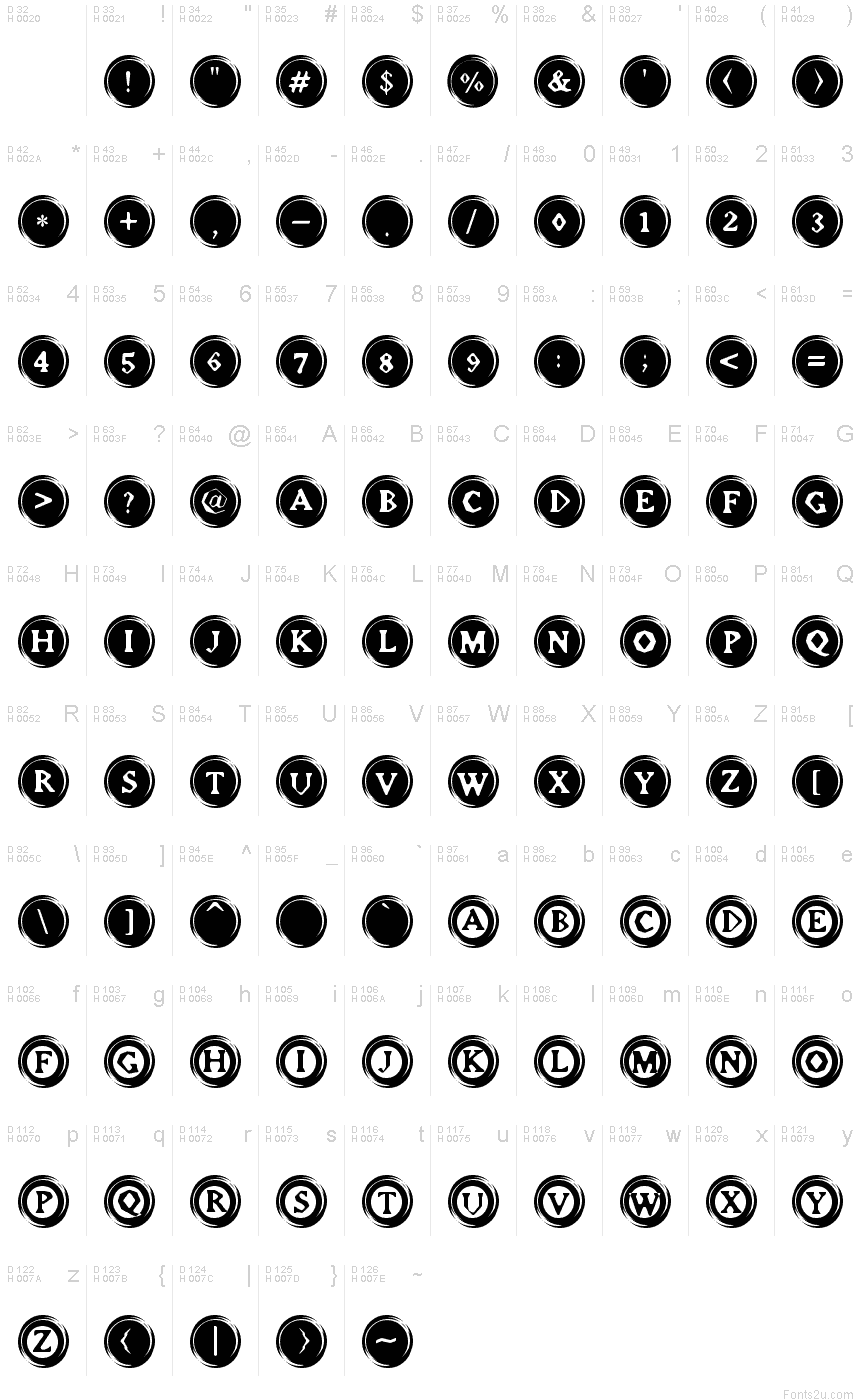
Elevator Buttons od OMEGA Font Labs to bezpłatny, dekoracyjny krój pisma, który przypomina rządek błyszczących, podświetlanych przycisków windy. Każdy znak umieszczony jest w gęstym czarnym okręgu z warstwowymi białymi obwódkami, tworząc mocny, „przyciskowy” rytm, który wręcz wyskakuje ze strony. Masywne, lekko nietuzinkowe litery przypominają połączenie panelu sterowania w stylu retro z automatem do gier, nadając nagłówkom wyczuwalną, interaktywną energię.
Wykorzystaj Elevator Buttons do błyskawicznego brandingu interfejsów gier, plakatów sci-fi, paneli sterowania, tytułów imprez tematycznych, grafik do escape roomów czy nietuzinkowych opakowań. Ten bezpłatny font najlepiej sprawdza się w dużych rozmiarach, gdzie okrągłe odznaki mogą w pełni wybrzmieć; połącz go z prostym, geometrycznym krojem bezszeryfowym w tekście głównym, aby zachować przejrzystość i czytelność projektu.